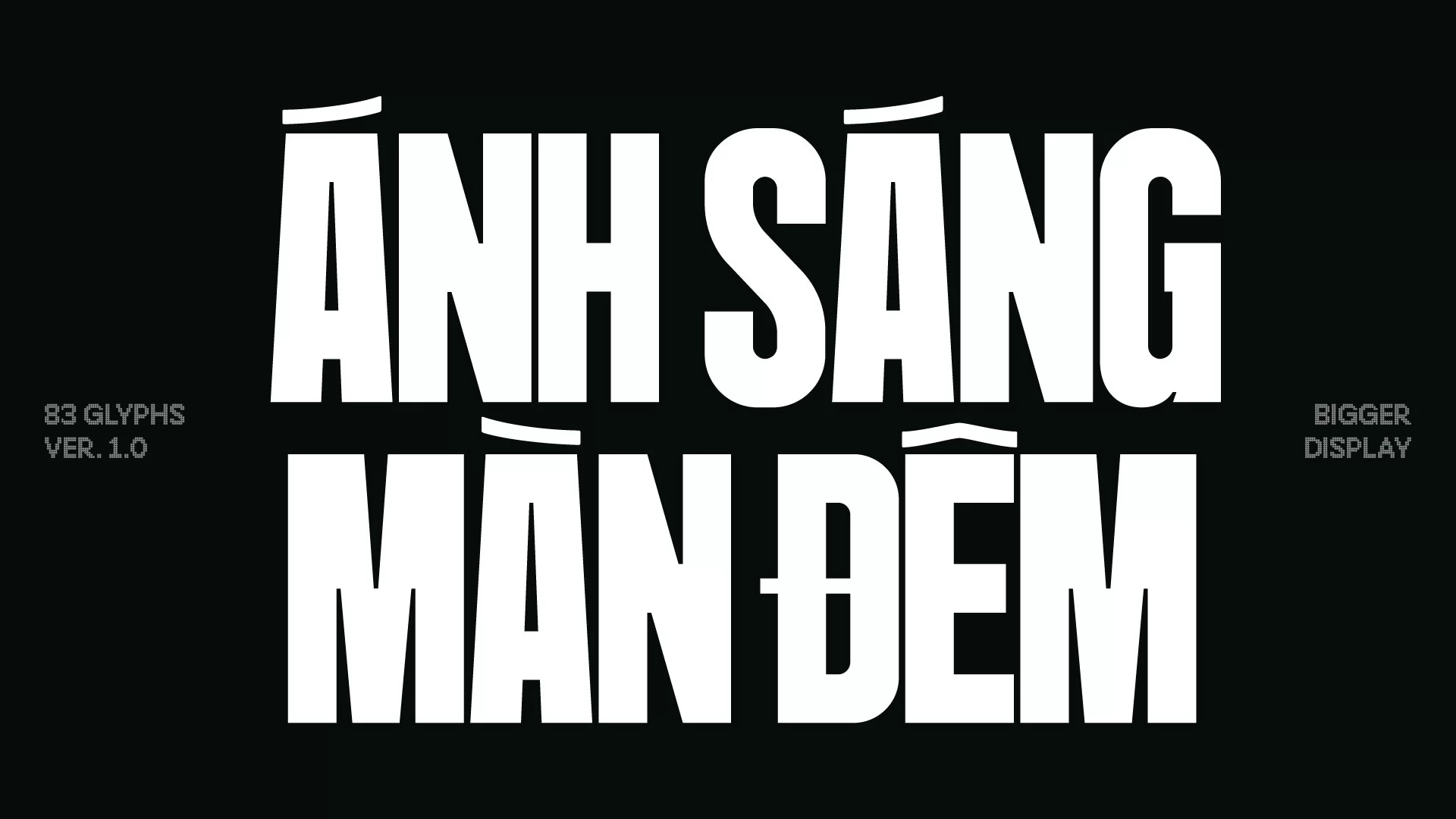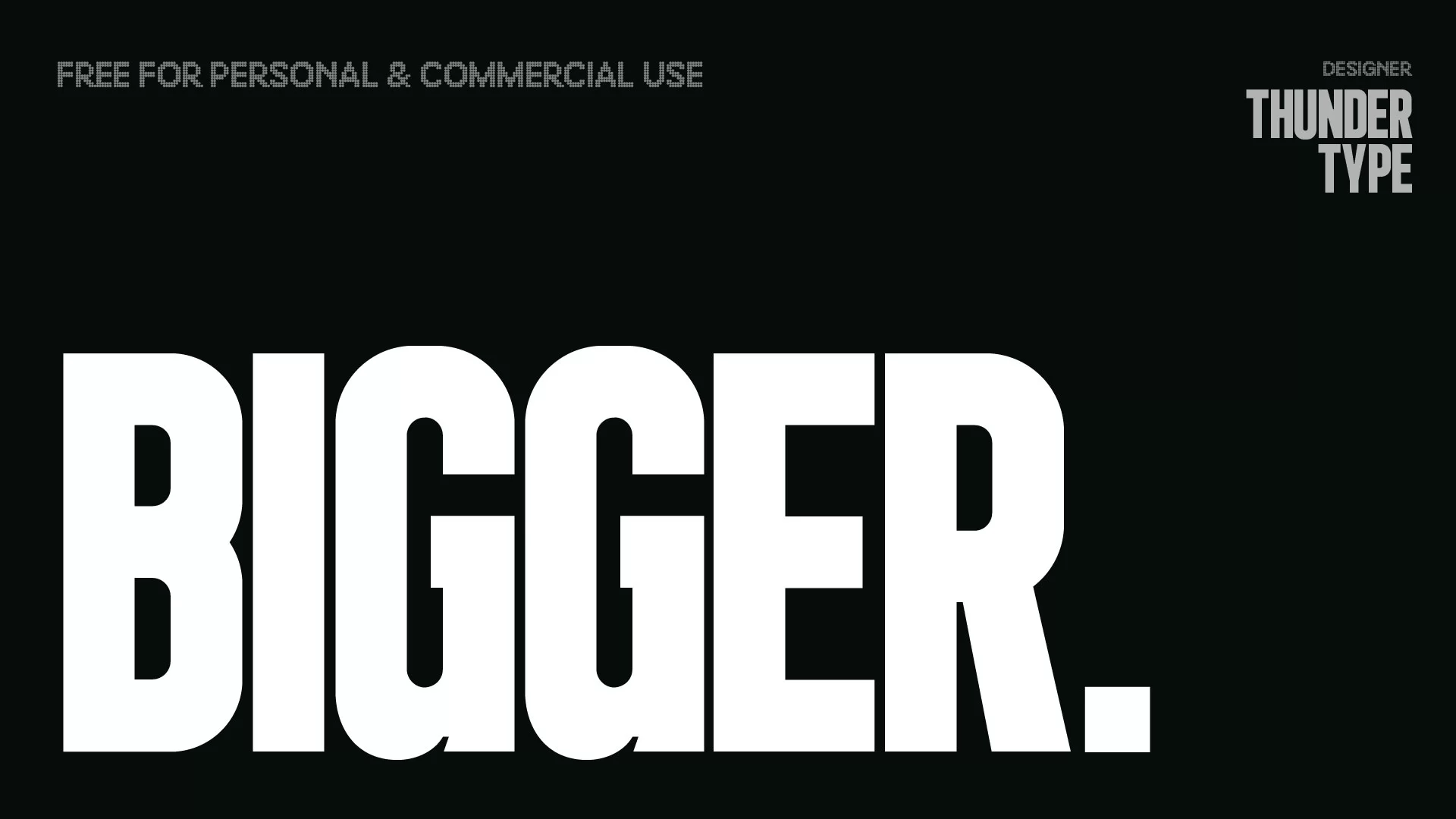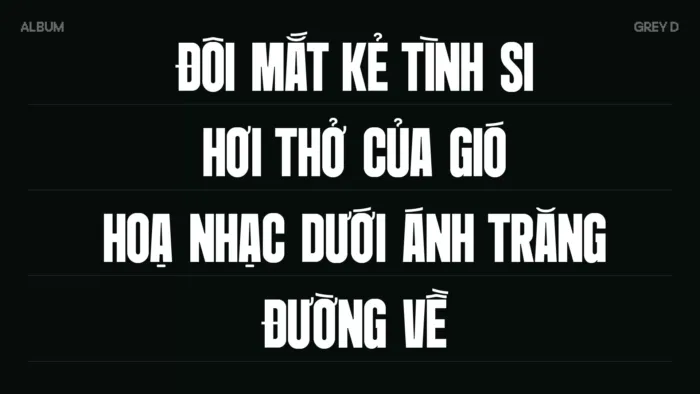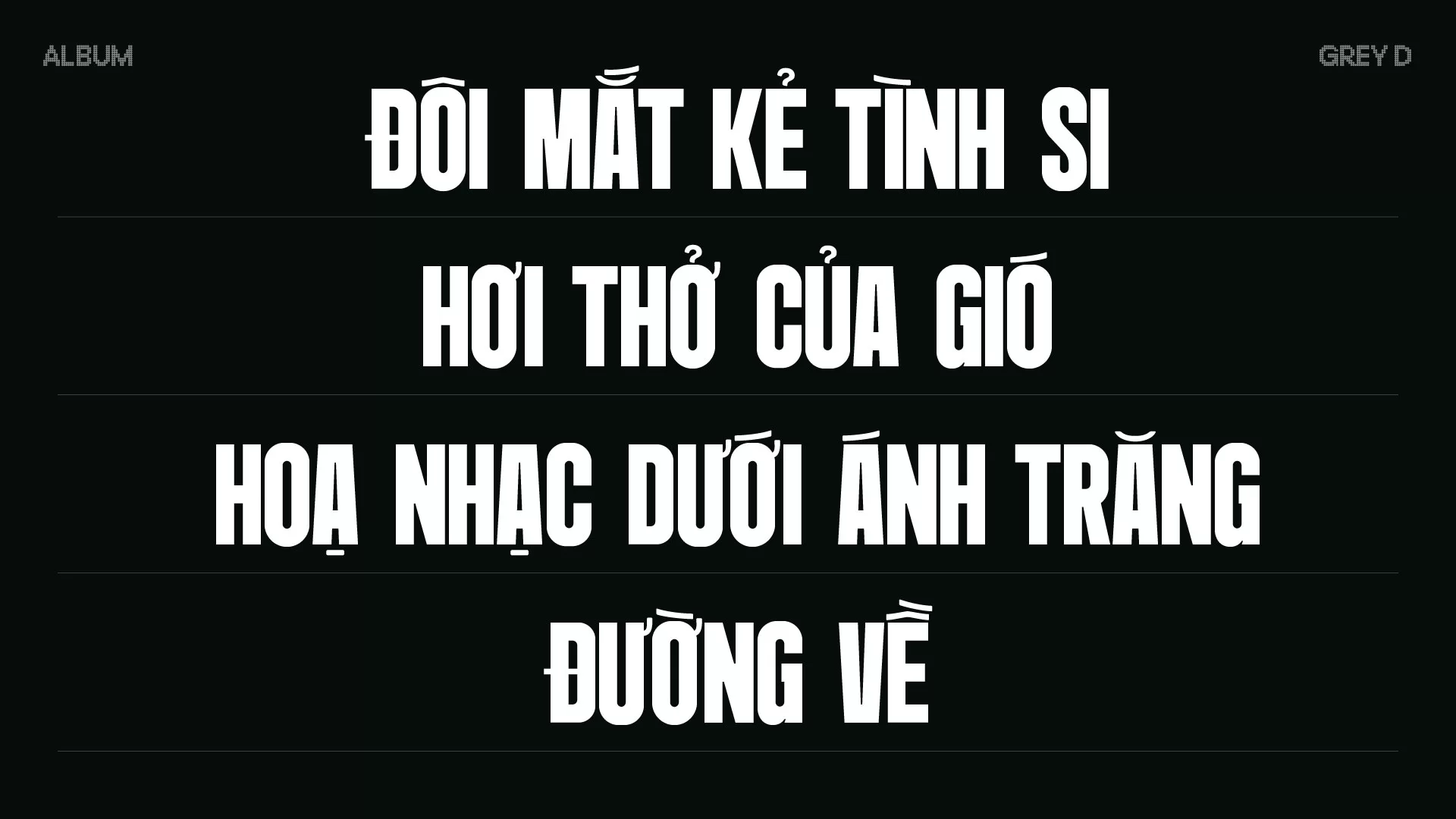
PS BIGGER – Font Display Việt Hoá tốt cho tiêu đề
Bigger Display là kiểu chữ condensed được thiết kế bởi Thunder Type, nổi bật với tỷ lệ hẹp, độ đậm cao và cấu trúc vuông vức mạnh mẽ. Các chi tiết khe hở đặc trưng giúp font mang cảm giác hiện đại, cá tính và thu hút ở kích thước lớn.
Font phù hợp cho headline, poster, thumbnail YouTube, quảng cáo và các thiết kế cần độ nhận diện cao. Bigger Display chỉ hỗ trợ chữ in hoa (Uppercase), vì vậy cần bật Caps Lock khi sử dụng.